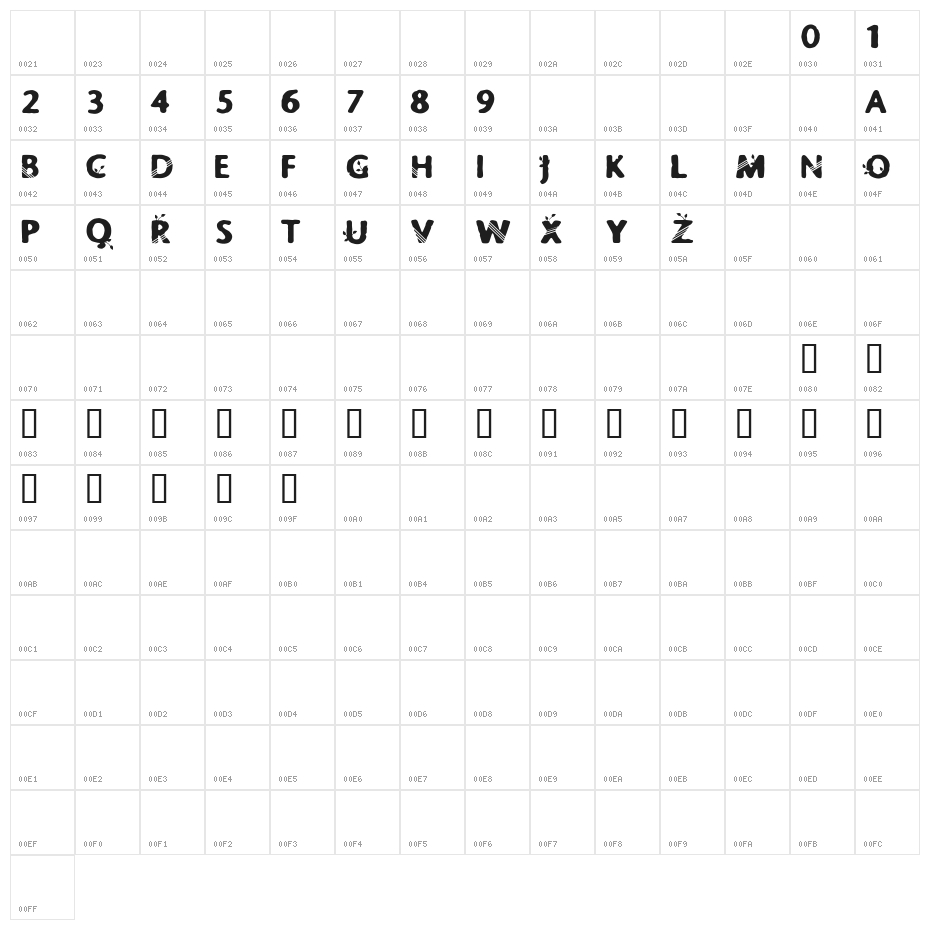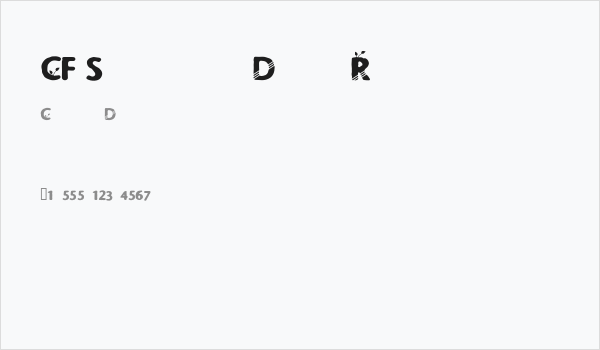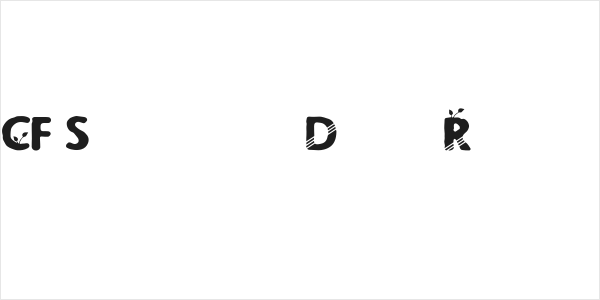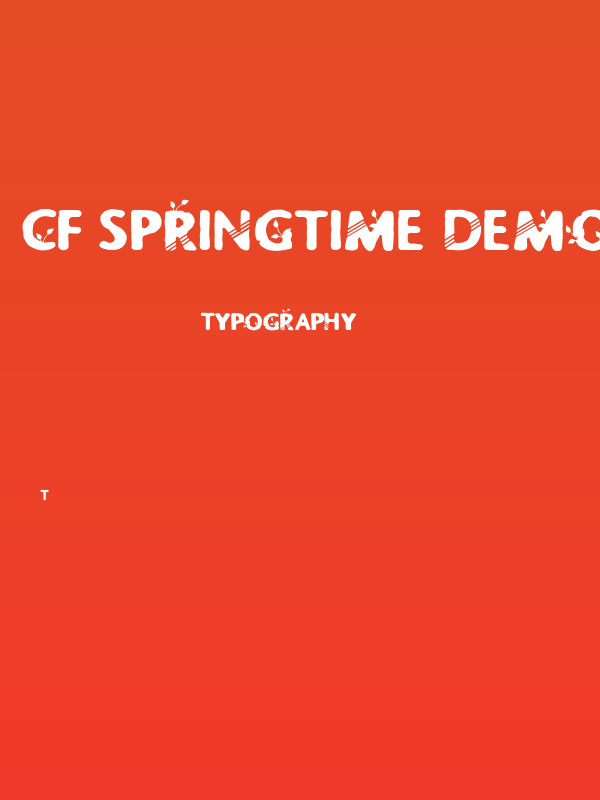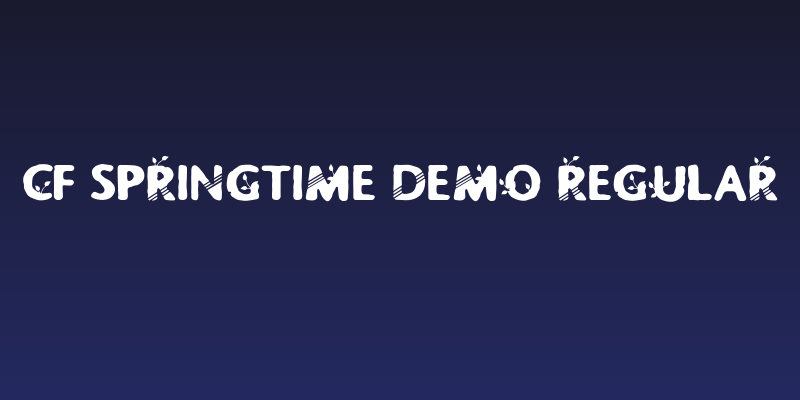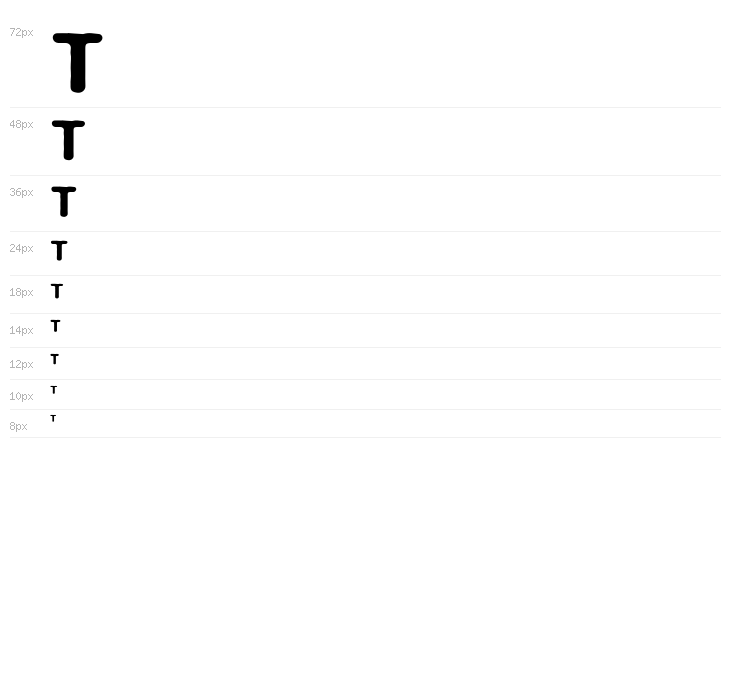
CF Springtime Demo Regular Font
| Proyectos propuestos | Ideal for greeting cards, spring-themed posters, children's books, and eco-friendly brand logos. |